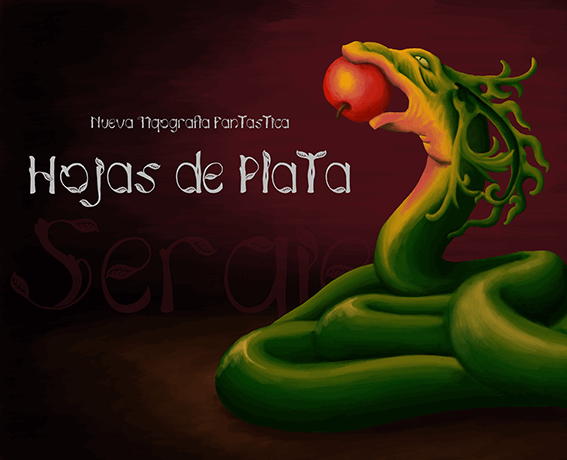
A Hojas de plata é uma fonte decorativa desenvolvida pelo designer Hamilton que traz características únicas para a sua página de download. Com seu design delicado e elegante, essa fonte se destaca como um excelente complemento para qualquer projeto de gráfica. Suas bordas bem trabalhadas e linhas finas evocam o brilho da prata, proporcionando um toque sofisticado que enriquece seus projetos sem ser excessivo. Ideal para aplicativos que requerem um toque elegante ou formal, esta fonte oferece um contraste perfeito com os textos mais sutis, tornando-a uma opção ideal para criações gráficas de alto padrão. Como sua descrição original sugere, ela é perfeita para quem busca trazer nuances e detalhes em seus trabalhos digitais de forma profissional e criativa.